Las mejores tipografías de números para que dejes de usar Arial
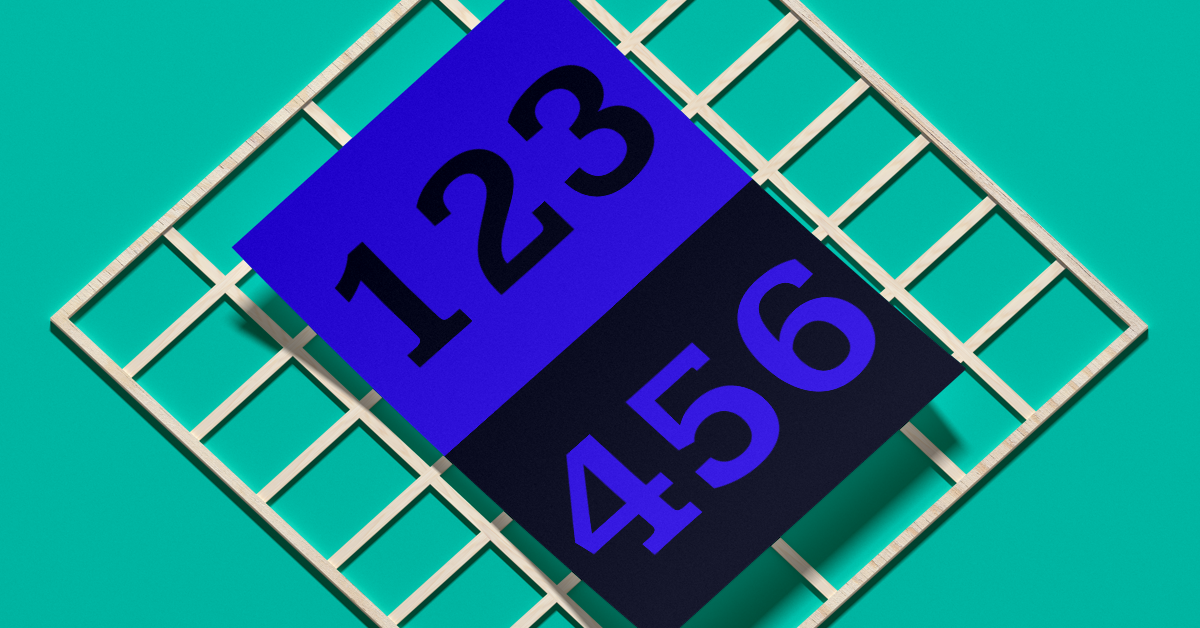
Todo buen diseño tiene una imagen perfecta, medidas precisas, colores con armonía y una tipografía adecuada. Sí, tu tipo de letra no puede desencajar y es sumamente importante para el mensaje que quieres transmitir. Así que, en este artículo te presentaremos las mejores tipografías de números para que tus diseños queden top 🔝.
Deja de utilizar Arial o Comic Sans para todo y descubre estas tipografías para números.
¿Por qué son importantes las tipografías de números?
Seamos honestos, lo último que definimos cuando creamos un diseño es el tipo de letra. Preparamos la foto, la editamos, agregamos formas y luego solo añadimos la letra “que vaya mejor”. Esta práctica no es la mejor si quieres convertirte en un profesional del diseño. Las tipografías para números existen porque cumplen la función de transmitir correctamente un mensaje.
Te sugerimos que cambies un poco el orden de las cosas y consideres importante tanto la fotografía que vas a usar como la tipografía de números que utilizarás, por ejemplo, en el diseño de una camiseta o una banderola. A propósito, descubre cuál es la tipografía de la camiseta de Lionel Messi, Diego Maradona y más.
¿Qué transmiten los números? Mucho. Al igual que las palabras, los números cargan mensajes que siempre tienen una consideración de valor. En el fútbol, el 10 del equipo es el creativo, en los rankings, el/la número 1 es el/la mejor. Esta importancia ha hecho que muchos diseñadores busquen tipografías de números para que su trabajo sea profesional.
¿Por qué usar tipografías para números?
- Para capturar la atención del público hacia los diseños.
- Para tener un símbolo correcto y adecuado que represente lo que quieres transmitir.
- Las tipografías para números no dejan dudas entre símbolos. Por ejemplo, el cero con la o.
- Para hacer el trabajo de diseño más profesional. Los detalles de las tipografías de números aumentan tu profesionalismo.
Además, si estás involucrado en un proyecto de ventas donde debes mostrar un catálogo con precios, lo correcto es que busques el mejor tipo de letra para números.
Tipografías de números para tatuajes
Cuando hablamos de tipografías de números para tatuajes, debes considerar el carácter o sentimiento que quieres transmitir. Claro, porque si quieres hacerte un tatuaje rudo o sexy el tipo de letra será fundamental para transmitir tu idea.
En el caso de las tipografías de números para tatuajes, hay que probar cómo se verá el tatuaje en la piel e incluso los colores que se usarán. Para hacer esto, considera imprimir en una hoja el tatuaje e imaginarlo sobre la piel. Porque no es lo mismo tipo de letra para títulos que una tipografía de números para tatuajes.
Para que no falles en esa huella para toda la vida, aquí te presentamos algunas tipografías de números para tatuajes que te serán de ayuda en tu diseño.
Tipografías de números para tatuajes: Beech
Beech es un tipo de letra que transmite fuerza y elegancia. Con siluetas similares a una flama, Beech es una tipografía de números para tatuajes por sus signos gruesos.
La fuente precisa para un tatuaje en color negro. Además, por sus curvas, siempre lucirán bien en cualquier superficie de la piel.
Tipografías de números para tatuajes: Blackletter
Blackletter es la tipografía para números si quieres algo inusual. Su estilo de curvas y puntas hacen que el tipo de letra transmita fuerza y un poco de agresividad.
Si alguien quiere transmitir rudeza, Blackletter en la tipografía de números que debe utilizar. También, es la fuente adecuada si quieres diseñar o hacerte un tatuaje solo negro. Por el grosor de la tipografía, el tatuaje te quedará muy bien.
Tipografías de números para tatuajes: Cute Tattoo
Si quieres una tipografía para números, Cute Tattoo te puede interesar. Con trazos delgados, curvas y una raya transversal siempre, busca hacer sentir una dulzura especial.
Si no quieres trazos gruesos, Cute Tattoo es una buena opción para ti. Además, sus números tienen formas muy especiales, parecerían que se están moviendo.
Tipografías de números romanos para tatuajes
Roman SD es la tipografía precisa si lo tuyo son los coliseos y gladiadores. Sabemos que cuando se trata de gustos, algunos prefieren lo clásico y singular. Por esta razón, en algunos diseños prefieren tipografías de números romanos para tatuajes.
Si eres el diseñador o el que se va a tatuar, te recomendamos que hagas una doble revisión de esta tipografía de números romanos para tatuajes. Ya sabes, no queremos que te equivoques. Por si acaso, acá un ejemplo sencillo: V = 5. Ten cuidado, luego no estés corrigiendo el tatuaje.
Vintage find es la fuente que buscas si lo tuyo es lo clásico. Esta tipografía parece una mala impresión con máquinas antiguas. ¿Conociste las máquinas de escribir? Entonces esta tipografía de números vintage te va a encantar. ¿Quieres más? Revisa estas 30 fotografías vintage que le van a gustar a tu abuelita.
Ya lo sabes, la tipografía de números es especial y necesaria para que tu mensaje llegue completo a quienes te diriges. Aprovecha todas las opciones que te dimos y si eres diseñador, descarga estas tipografías y aprovéchalas para sorprender.